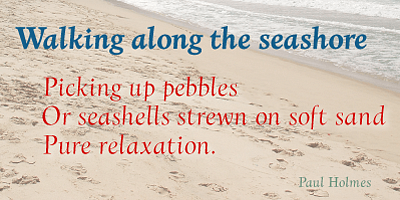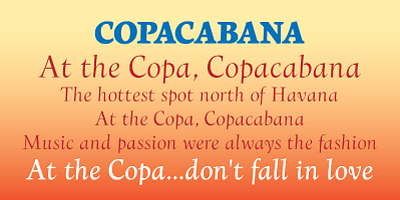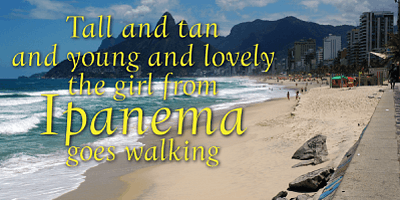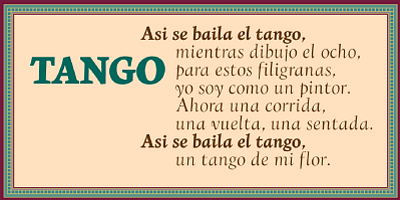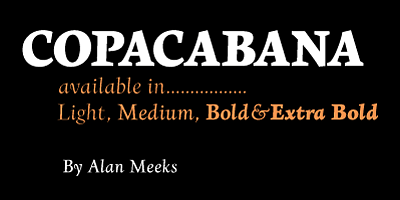
「Copacabana」は、私のお気に入りの書体「Goudy Old Style Italic」をベースにしています。「Goudy」よりもシャープで、輪郭が際立っていますが、古いスタイルの特徴が残っています。この書体はやや傾斜しています。よって、基本的には直立していますが、イタリックの特徴はそのままです。